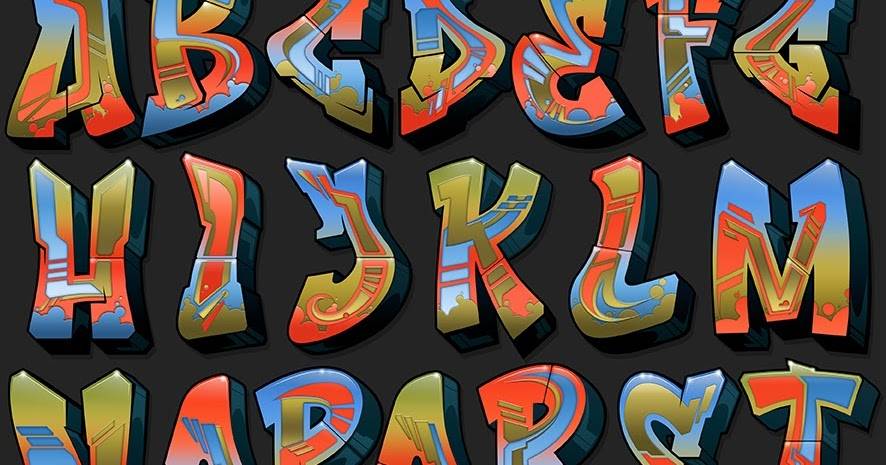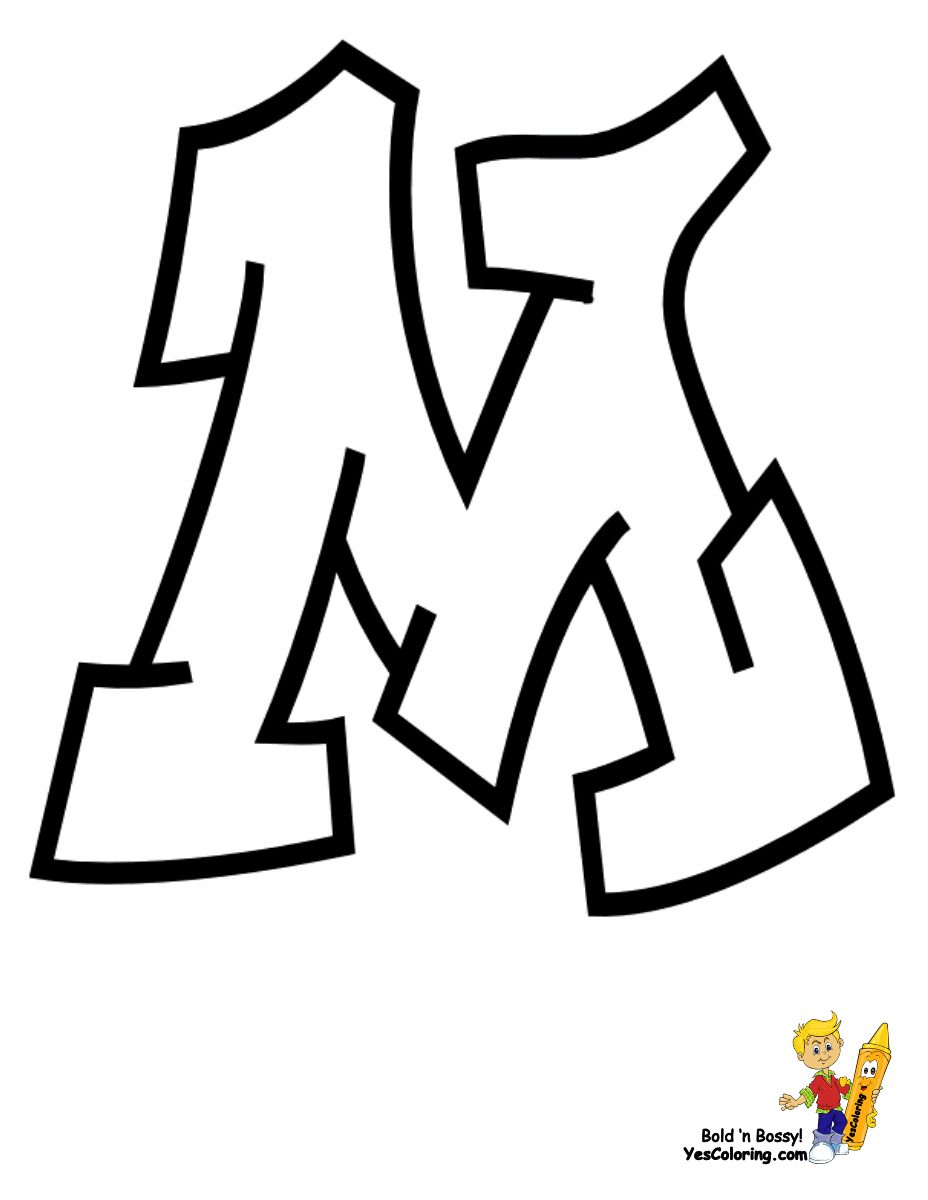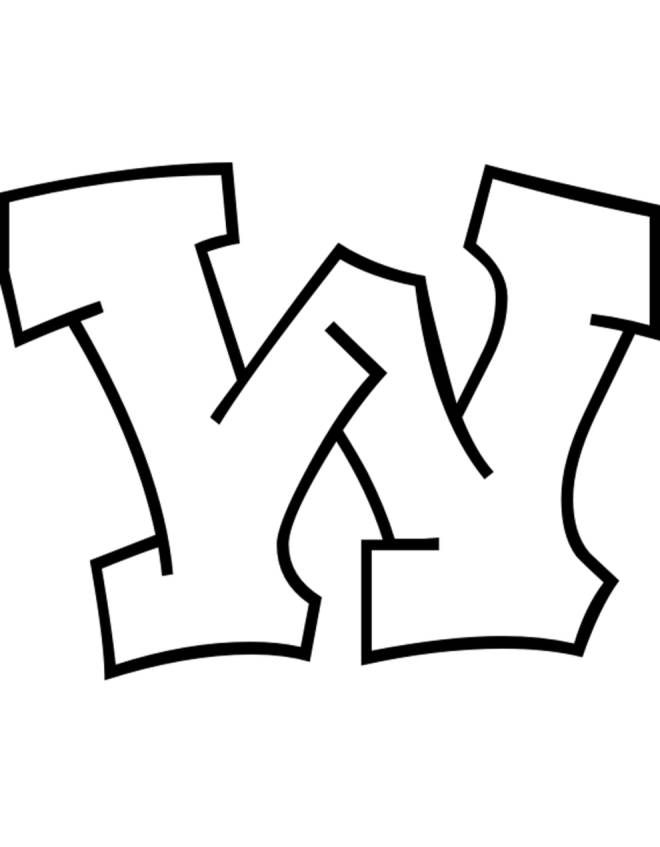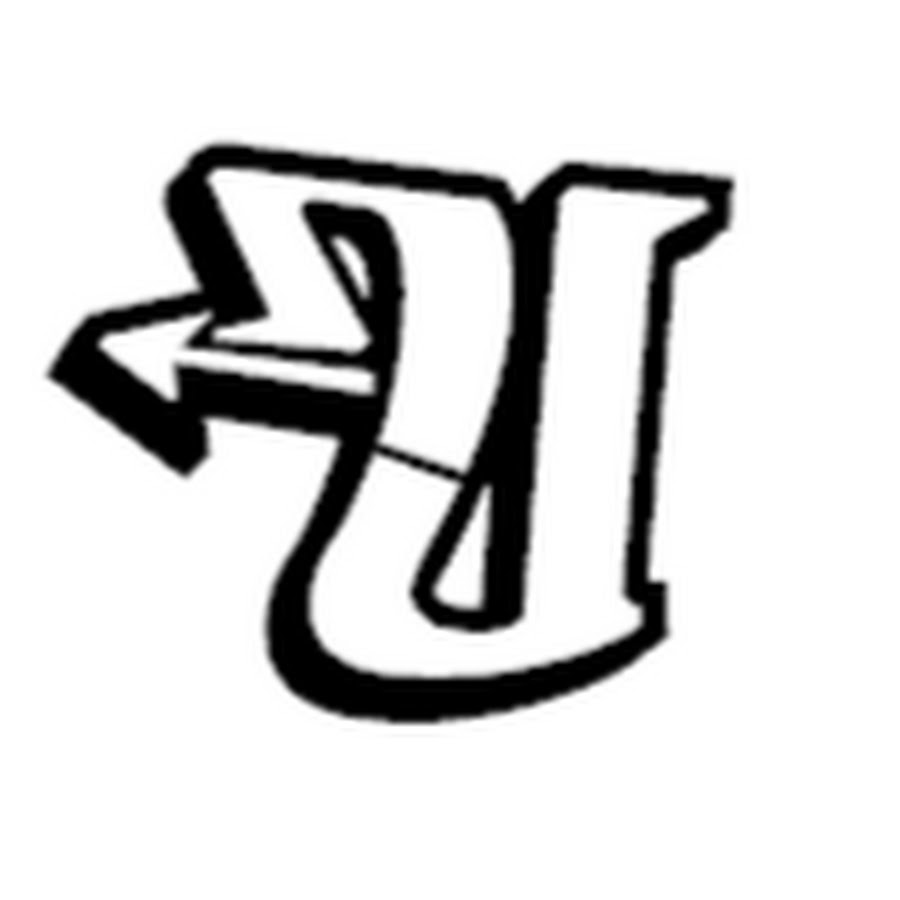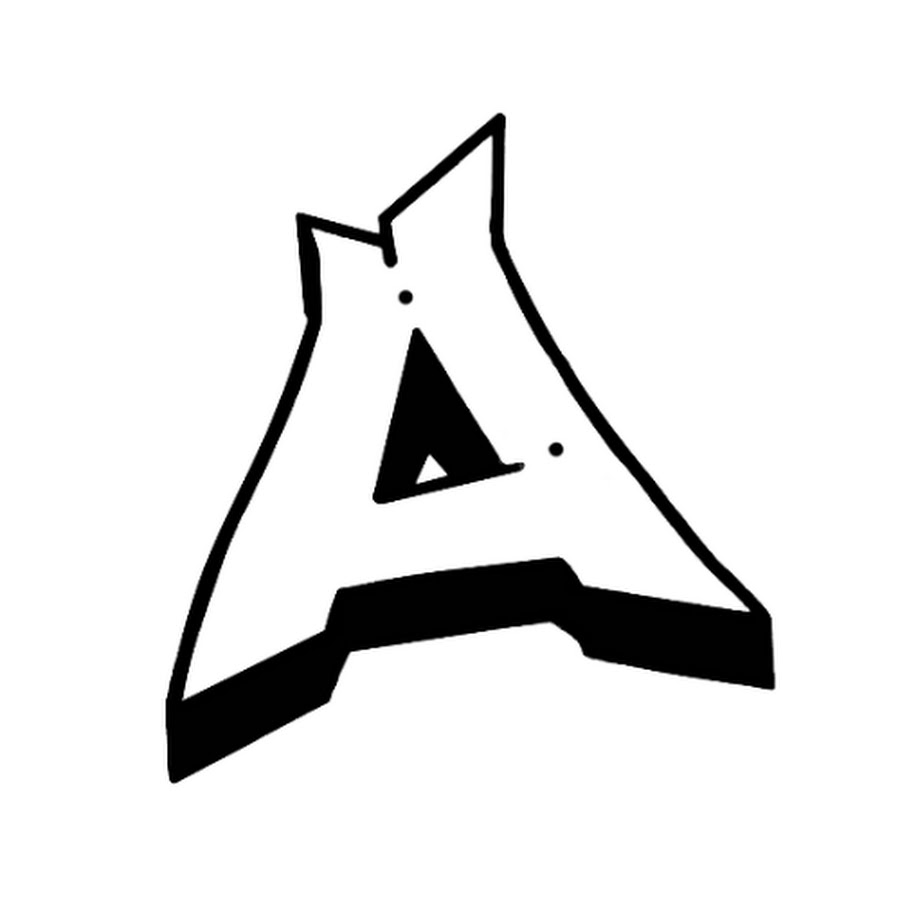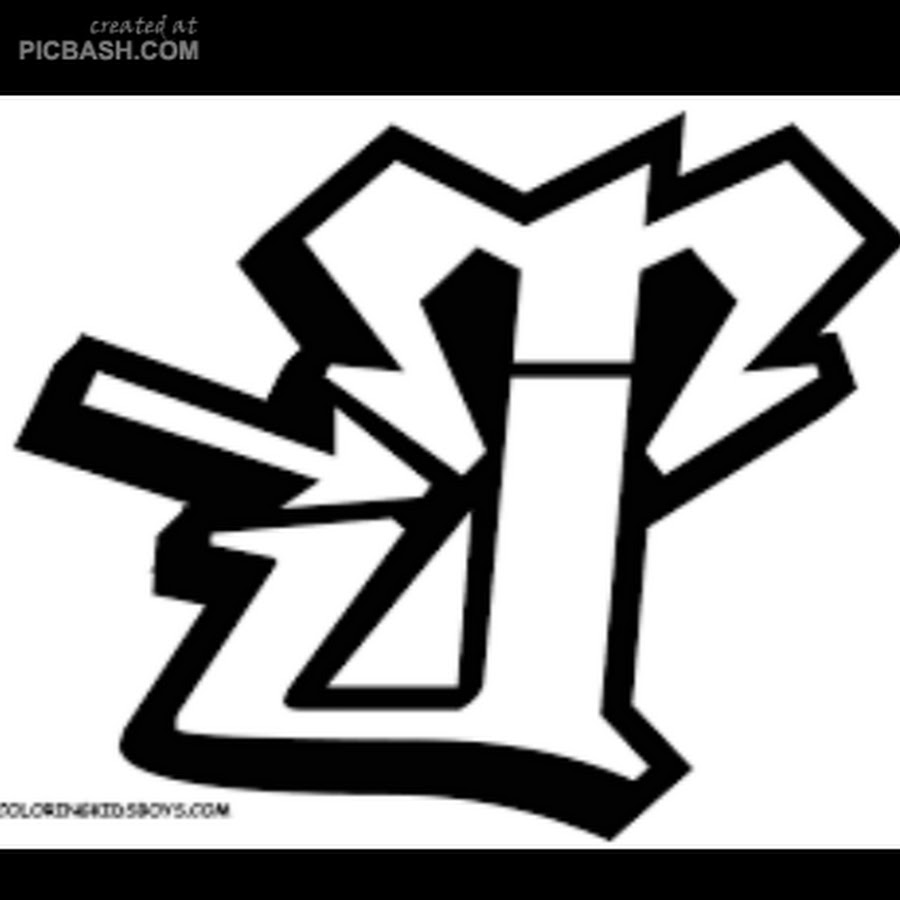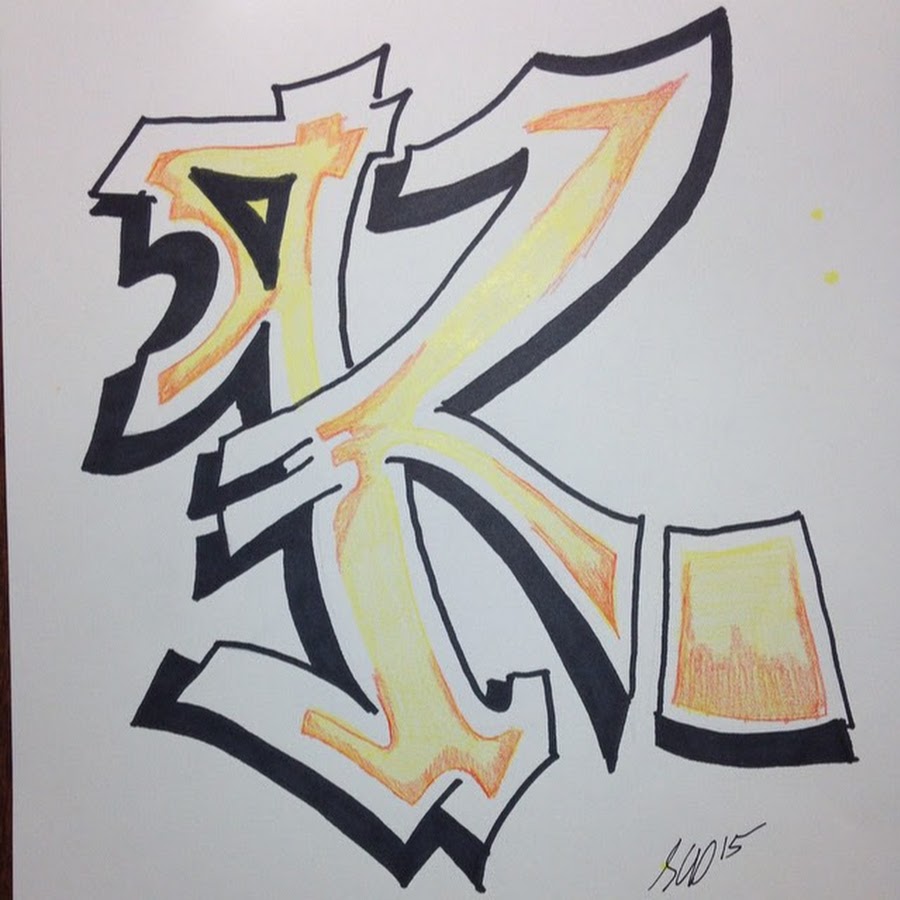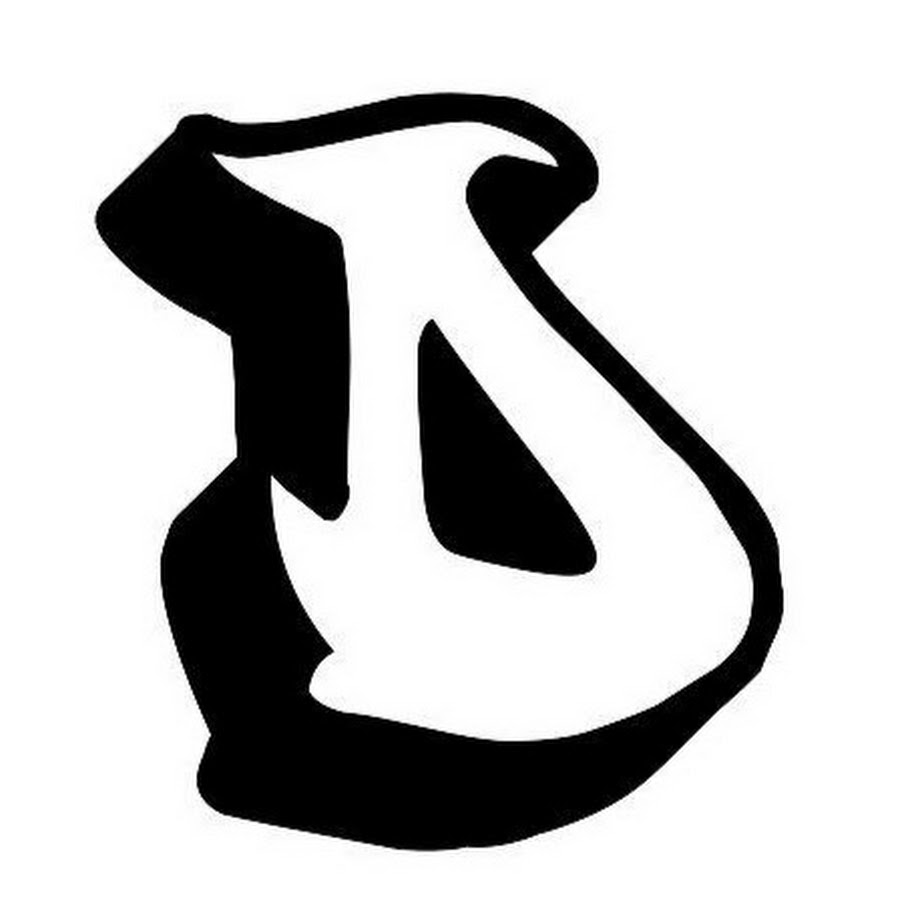
Лучшие шрифты граффити
Существует огромное количество граффити-шрифтов — как традиционных, так и авторских. Есть даже специальные сайты, которые разрабатывают новые формы и стили букв для начинающих художников. В наше время найти их довольно легко. Но со всем этим обилием информации справиться иногда не так то просто, поэтому мы перелопатили не один ресурс и вспомнили работы не одного десятка легендарных художников для того, чтобы собрать для вас лучшие шрифты граффити со всего мира.
Топ-30 лучших шрифтов граффити
30. Ruthless Drippin One — очень красивый художественный шрифт, разработанный Mans Greback. В нем сочетаются тонкие и толстые линии, которые придают буквам своеобразных форм. Также особенностью этого шрифта является большое количество потеков, добавляющих ему эффектности.
29. XXII YeahScript RegularЭтот шрифт разработан человеком по имени Lecter Johnson и отлично подходит для написания различных заголовков, текстовых фраз, создания тех или иных лого и т.
д. Он имеет большое количество вариантов написания букв и много других опций.
Kwaktur — современный шрифт граффити, доступный в трех разных вариантах: Kwaktur, Kwaktur Shadow и Kwaktur Shadowonly. Каждый из них прекрасен по-своему и имеет свои элегантные особенности в написании. Создан Dave Rowland.
27. Dim Basic — это классический и стильный шрифт, который хорошо подходит для любого типа проектов. Он имеет округлые формы, интересный угол наклона букв и много разных вариантов их совмещения. Этот шрифт является подтверждением того, что очень часто простота имеет преимущество над художественными изысками.
26. ThrowupzОдин из самых привлекательных граффити-шрифтов Mans Greback, обладающий “баббл-формами” и имеющий множество крутых дополнительных элементов. Он напоминает классический нью-йоркский стиль и используется художниками по всему миру.
25.
Paint CansЭтот шрифт имитирует буквы, нарисованные широкой кистью. Его автор Matthew Napolitano создал уникальный инструмент для уличных художников, добавив в него множество особенностей, главной из которых являются смазанные края букв. Такой элемент небрежности придает им некий шарм и выгодно выделяет среди большинства других шрифтов.
24. Degrassi — еще один стильный и вдохновляющий шрифт граффити, который больше подходит для воплощения в жизнь комичных или мультяшных концепций. Буквы здесь имеют острые края стрелко-подобной формы. Разработан Ray Larabie.
23. HumgerВ отличии от большинства в этом списке, Humger — это абсолютно бесплатный шрифт, который можно скачать в сети просто так. В нем легко можно увидеть огромное влияние старомодных шрифтов-трафаретов. Также особенностью Humger является то, что в нем все буквы заглавные. Этот шрифт разработан ливанским художником Wassim Awadallah, который выставил его для свободного использования как в личных, так и в коммерческих целях.
Mustang — “острый” и очень выразительный шрифт, созданный Robert Arnow. Несмотря на свое “мужское” название, в нем чувствуется определенная женственность. Небрежные (но прекрасно продуманные) формы, словно написанные в тетради от руки, прекрасно подойдут для разных типов проектов. Часто используется в рекламе.
21. GhangGhang — еще один четкий шрифт от Mans Greback, который имеет достаточно интересную форму букв и годится для необычных надписей.
20. KaligraffЭтот шрифт выглядит так, будто как минимум наполовину написан от руки. От этого и название. Он имеет эффектный наклон букв и крутые дополнительные штрихи в их написании.
19. HawkeyeHawkeye — прекрасный, богатый на вид шрифт от Ray Larabie. В первую очередь в нем выделяются тени букв, придающие им объем. Часто используется для написания заголовков.
18. Ruthless WreckingОдин из наиболее впечатляющих граффити-шрифтов, который используется абсолютно в разных областях искусства, но при этом всегда несет в себе “уличную” эстетику.
Имеет невероятно привлекательную форму букв и вариантов их комбинирования вместе.
Graffiti Treat — очень популярный шрифт граффити, имеющий некий уклон в олд-скул. Буквы здесь хорошо различимые, но имеют много интересных “заковык”. Именно они придают Graffiti Treat уникальности. Редко используется в коммерческих целях, чаще встречается на городских стенах.
16. Black TopОчень симпатичный шрифт — простой и универсальный, но при этом, обладающий своими стилевыми особенностями. Разработчик — SixAbove Studios. Парни сделали Black Top бесплатным для персонального использования.
15. Vandalism Alternate — это смесь артистического подхода и классической манеры написания букв, которая в итоге дарит нам великолепный граффити-шрифт со слегка небрежными краями букв и приятными глазу изгибами. В нем отлично продумано расстояние между буквами и едва уловимые мелкие штрихи.
Абсолютно бесплатный шрифт, в котором объединились классический трафаретный тип букв с налетом научной фантастики. Это выражается в небольших точках, присутствующих практически на каждой букве, похожих на небесные тела. Разработан бразильским художником Pobrenerd.
Я выбрал диагональный поток писем.Слегка нарисуйте несколько ориентиров, где должны будут располагаться ваши буквы. Обычно я использую красный карандаш Col-Erase, потому что он не размазывается, как обычный карандаш. Однако сегодня я использую обычный карандаш, чтобы вам было легче видеть.
Рисуя буквы, вы должны убедиться, что вы заполняете как можно больше бумаги.
По этой причине вам нужно знать, где находится середина вашего слова. В слове «мечта» буква Е — это середина. Если в вашем имени или слове четное количество букв, средняя точка будет между двумя буквами.